Caracteres de néon no deserto
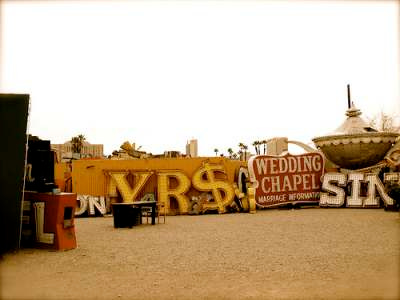
Tem uns lugares que são tão incríveis, mas tão incríveis, que às vezes tenho a sensação de era tudo invenção da minha cabeça e que eles não existem coisa nenhuma. E volta e meia vou conferir se eles continuam sendo de verdade ou se fui eu que inventei tudo.
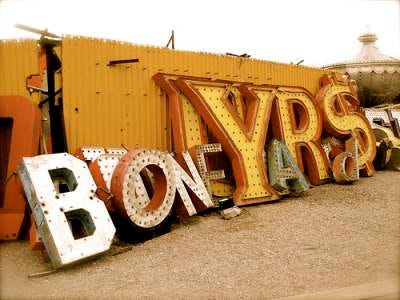
Esses dias eu fiquei bem feliz de cruzar com essas fotos do Boneyards do Neon Museum. Eu estive lá, mas mesmo assim já estava achando que ele era uma espécie de vale dos unicórnios atrás da cachoeira.
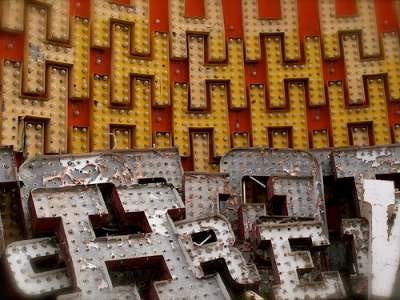
O Neon Museum fica em Las Vegas e funciona assim: todos os néons quebrados, queimados, velhos, à beira da morte, são levados para o Boneyards e ficam lá em vez de serem jogados no lixo. É um cemitério de néons. Alguns dos néons são recuperados e passam a ser expostos em Neonopolis, que fica na Freemont St, onde Las Vegas nasceu. Os néons quase mortos são ressucitados e pendurados onde a cidade nasceu.
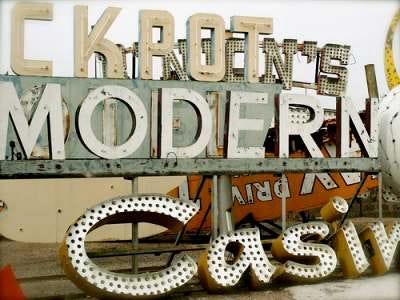
Las Vegas é no meio do deserto. E Boneyards fica numa espécie de estacionamento. Daí venta e a areia vem com tudo e enterra uma parte dos néons. Fica tudo parecendo ruína de um tempo em que Las Vegas era mais SinCity e menos Disney.
Neonopolis é um shoppingzinho alto, com uns 5 andares e um grande vão central. À noite, quando todas as lojas fecham, o salão fica aberto, e os néons continuam ligados. Resultado: os néons ficam ali pairando em uma espécie de túnel vertical. Parecem fantasmas de um tempo em que Las Vegas era menos Disney e mais SinCity.